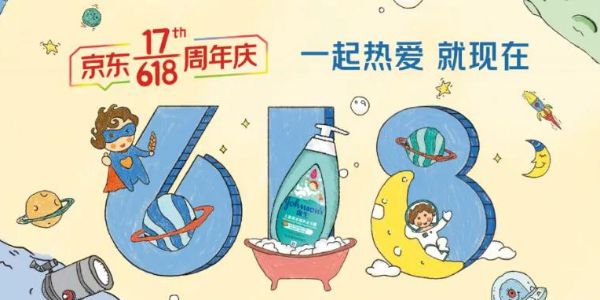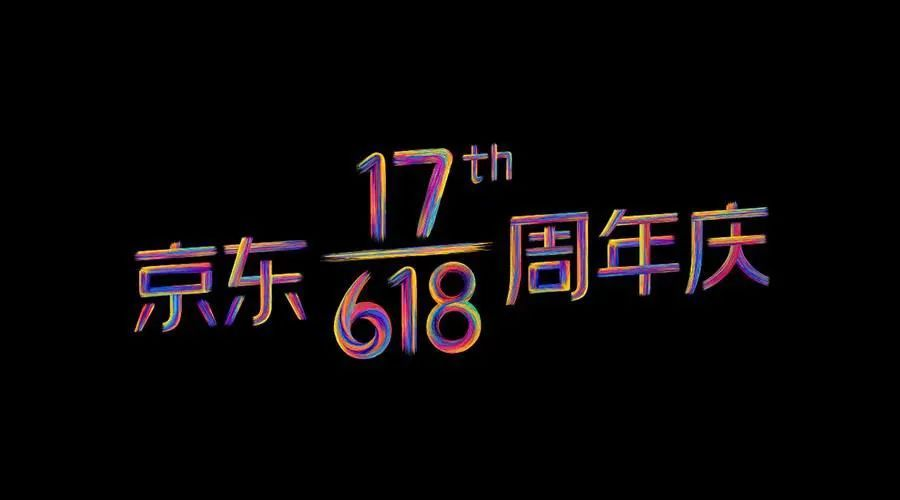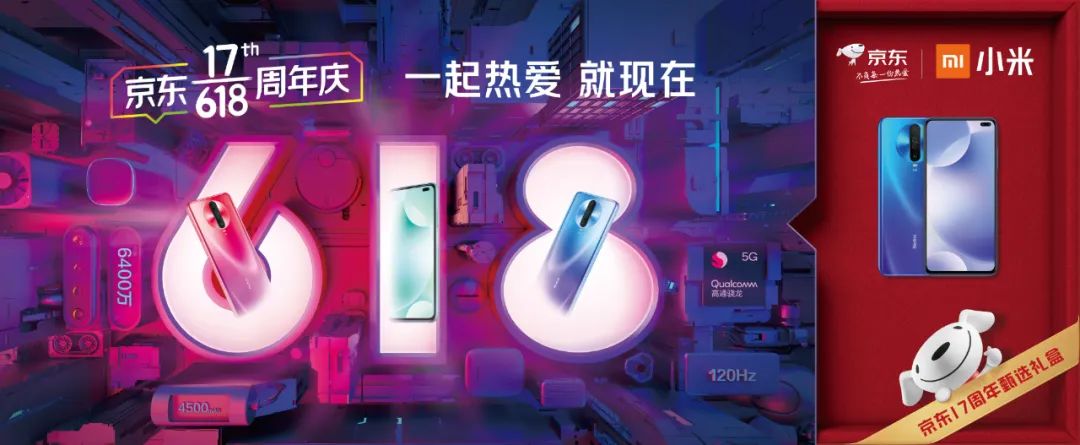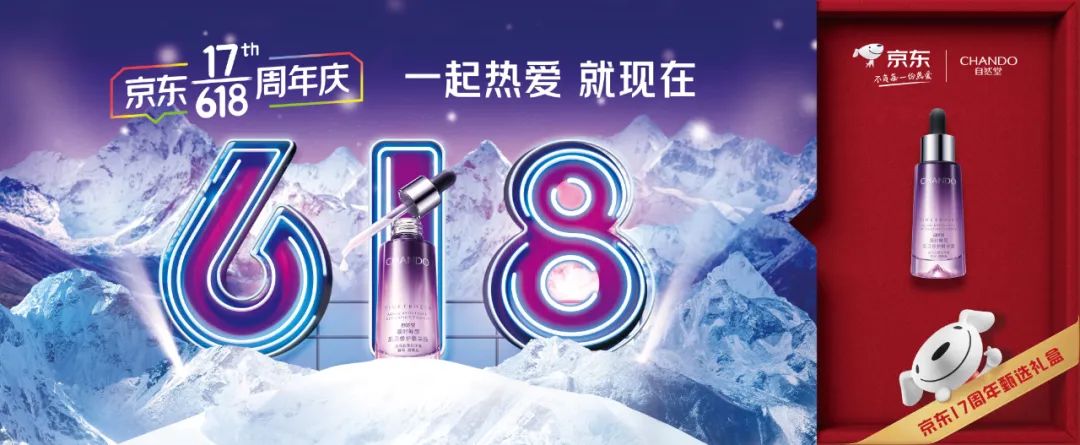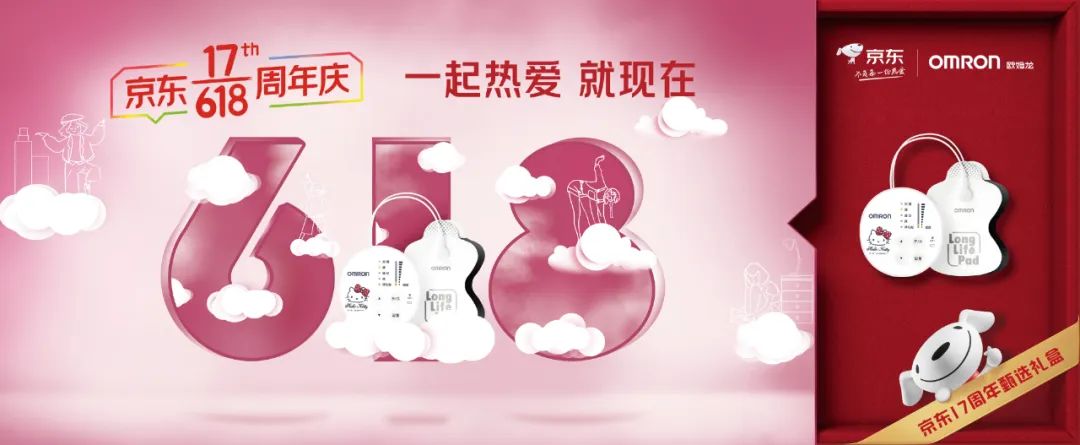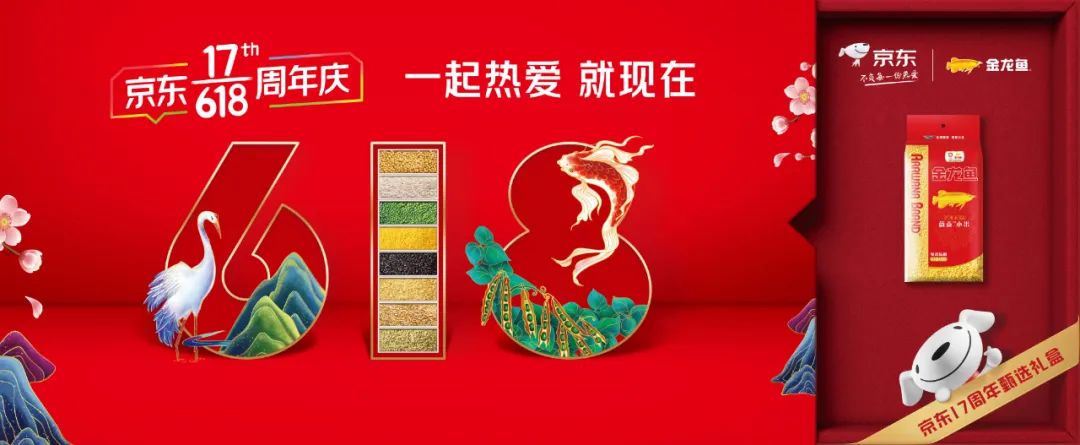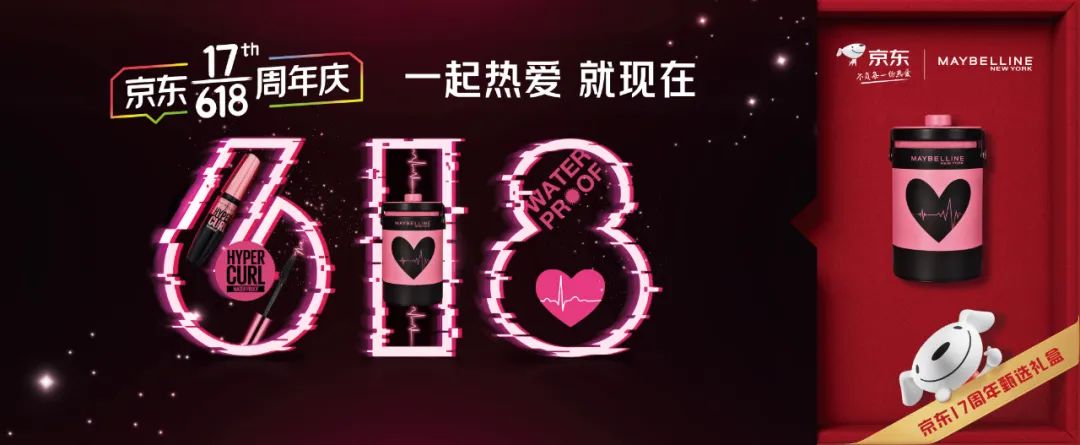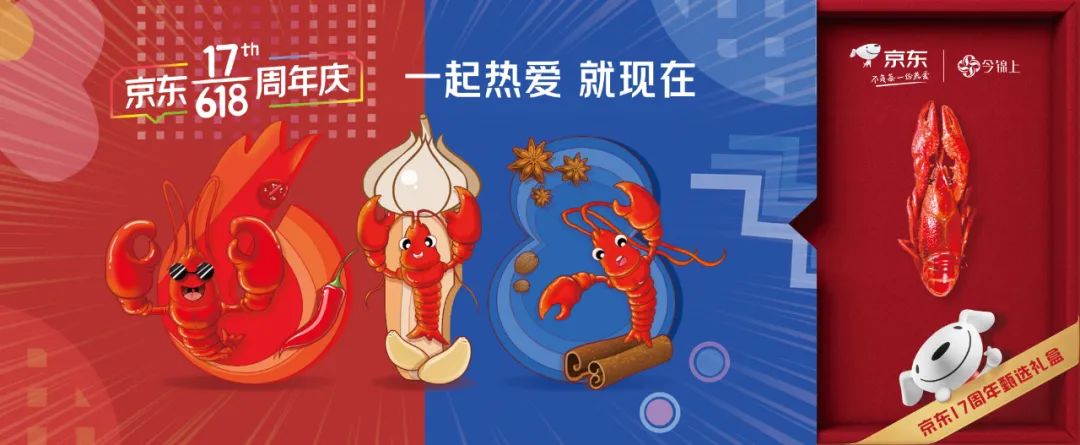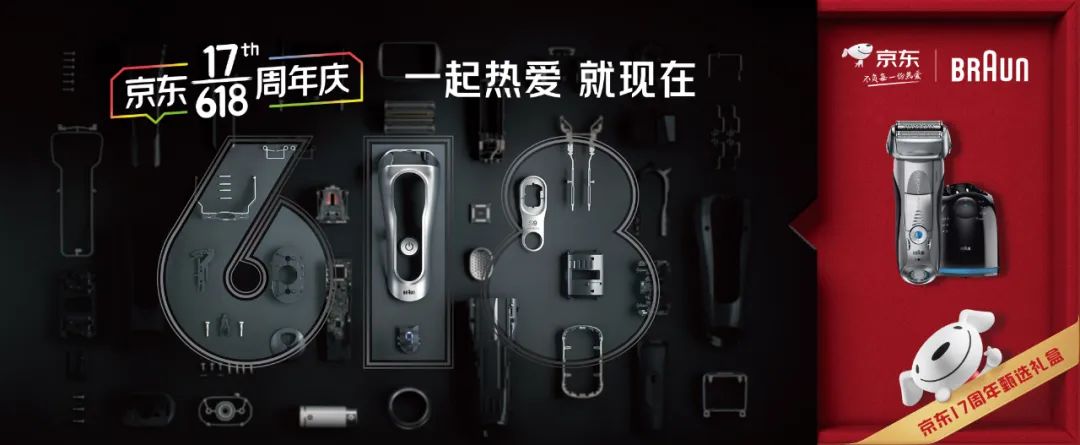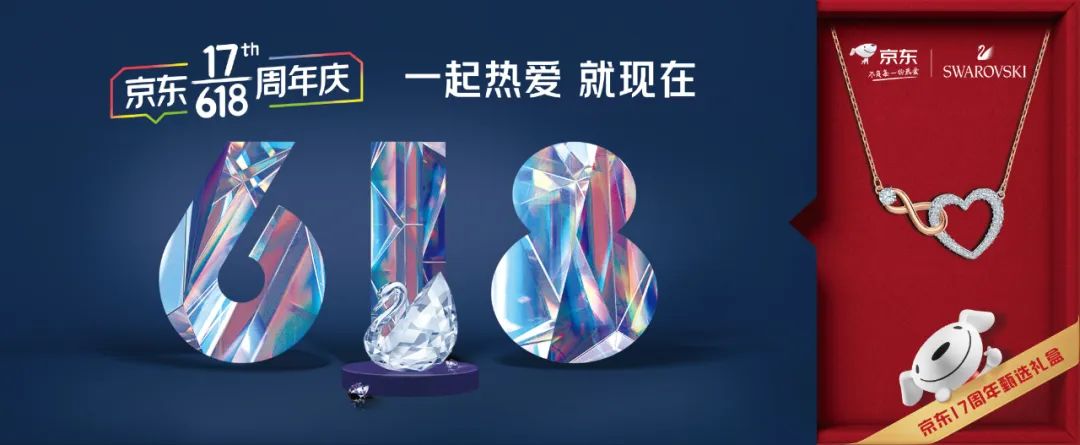
今年京东618品牌联合海报,有点强啊!
618终于要来了
几乎每年618大促
京东都会联合大品牌店铺
制作超级符号创意海报
这不,今年的已经来了
一起来看看!
小米
万能的C4D,舒服的配色
今锦上
产品与数字的结合度很好、生动有趣
BARAUN
聚光灯结合产品部件的创意很有意思
施华洛世奇
切割镜面的文字创意很有张力
iQOO
你能看出此IP创意是什么吗?
阿迪达斯
空间很强,618字符对比色很形象
荣耀
机械的科技风格,强悍
GoPro
涂鸦的风格跟产品匹配度很高
戴森
精致的图纸样式,让产品更鲜明、有特色
笑脸科技
水的素材与数字结合度很高,赞一个
百威啤酒
产品包装与618超级符号相结合,设计很整体
DELL
三维的创意很新颖,用色也舒服
Swisse
很棒的材质应用,大自然的感觉
大眼橙投影仪
小黄人的IP,3D电影风很有带入感
PHILIPS
很有创意的手绘风格
因为海报多的缘故
这里就逐一分析了,大家一起看看吧
金领冠
强生
雷士照明
Switch
天梭
乐高
中华商务
趣多多
Samsonite新秀丽
BOSE
Columbia
倍轻松
多趣酷思
PORTS
vivo
KARL
雪花秀
自然堂
膳魔师
PARZIN
欧姆龙
欧莱雅
金龙鱼
美宝莲
ROSEONLY
多芬
instax
Clanks
SONY
iRobot
欧舒丹
kindle
君乐宝
希宝
Honor
罗技
长虹电视
超级符号创意海报
已经成为大促活动的一大看点
能一直持续高质量的输出
设计师可谓功不可没